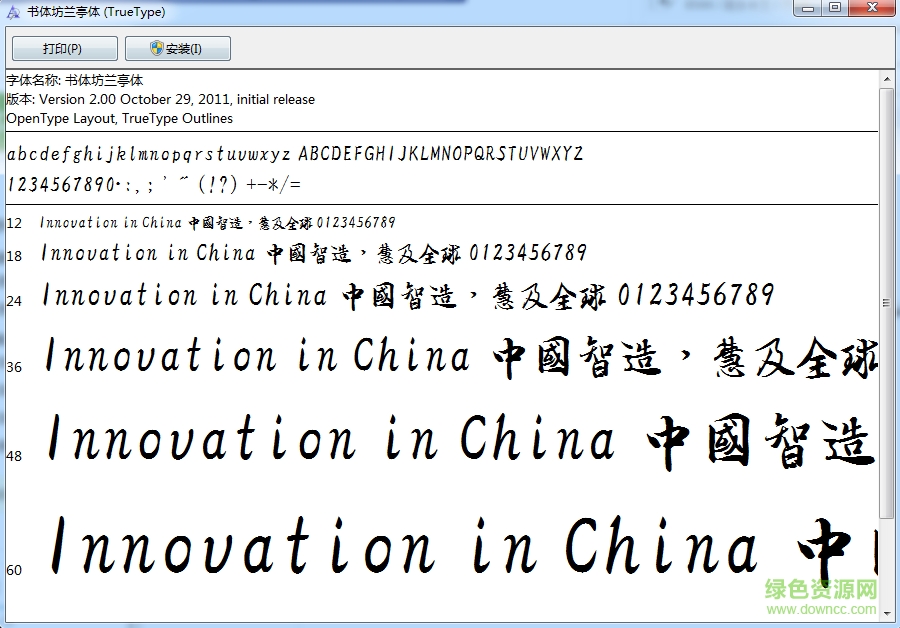
scfwxz是什么字體?scfwxz又叫書體坊蘭亭體簡體字體,是一款出自著名書法家王羲之作品的免費(fèi)書法字體,運(yùn)筆自然,遒勁不羈,極具美感,需要的朋友快來下載吧!
王羲之的《蘭亭集序》為歷代書法家所敬仰,被譽(yù)作“天下第一行書”。王兼善隸、草、楷、行各體,精研體勢,心摹手追,廣采眾長,備精諸體,冶于一爐,擺脫了漢魏筆風(fēng),自成一家,影響深遠(yuǎn)!其書法平和自然,筆勢委婉含蓄,遒美健秀!
草書是按一定規(guī)律將字的點(diǎn)劃連字,結(jié)構(gòu)簡省,偏旁假借,并不是隨心所欲的亂寫。草書符號的 主要特征之一是筆畫帶鉤連,包括上下鉤連和左右鉤連。